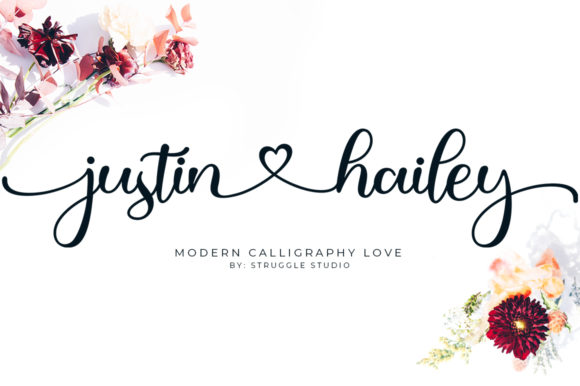
Justin Hailey Modern Font
Поиск подходящих элементов дизайна может быть сложным, но Justin Hailey Modern Font предлагает исключительную коллекцию, которая мгновенно улучшит вашу работу.
Созданный с высокой точностью, Justin Hailey Modern Font предоставляет чистые векторы, плавную типографику и коммерческую лицензию для вашего спокойствия.
Создаете ли вы продукты POD (печать по требованию), свадебные приглашения или графику для социальных сетей, Justin Hailey Modern Font станет идеальным выбором.